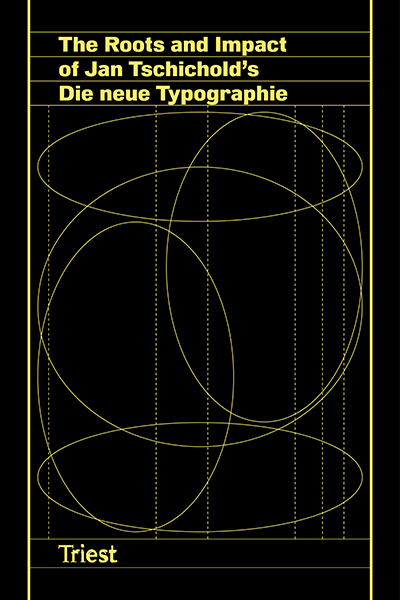
Davide Fornari, Chiara Barbieri, Jonas Berthod (Hrsg.)
The Roots and Impact of Jan Tschichold’s Die neue Typographie (Band 1)
Buchgestaltung: Federico Barbon
• Wo liegt der Urspung zu Tschicholds Werk und welche Strömungen hat es international beeinflusst?
Jan Tschichold war ein bedeutender deutscher Typograf, Buchgestalter und Schriftsteller, der als einer der Pioniere des modernen Grafikdesigns gilt. Geboren 1902 in Leipzig, entwickelte er innovative typografische Prinzipien und setzte sich für klare, funktionale Gestaltung ein. Sein bekanntestes Werk, Die neue Typographie (1928), bildete die Grundlagen des modernen Designs und beeinflusste Generationen von Designern. Tschichold war ein Verfechter der Verwendung von serifenlosen Schriften und einer strukturierten Anordnung von Text und Bild. Nach seiner Emigration aus Deutschland in den 1930er-Jahren setzte er seine Arbeit in der Schweiz und später in Grossbritannien fort, wo er weiterhin die typografische Praxis prägte.
In → Band 1 werden sowohl die Wurzeln, Quellen als auch die Auswirkungen der Neuen Typographie beleuchtet und gezeigt, wie Tschichold auf vorhandene Quellen zurückgriff, um seine eigenen Ideen zu formulieren. Die Essays erforschen die Ursprünge ähnlicher Prinzipien im frühen 20. Jahrhundert in Deutschland, der Tschechoslowakei und Dänemark. Die Publikation zeigt dann die Auswirkungen von Tschicholds Ideen auf die Gestalterszene weltweit, indem sie die Verbreitung, Rezeption und Nachwirkungen von Die Neue Typographie untersucht. Seine Ideen verbreiteten sich unmittelbar in der Schweiz, Grossbritannien und den USA, aber auch verschiedene nationale Szenen in ganz Europa und Asien griffen die Prinzipien der Neuen Typographie auf, wo sie angenommen oder neu verhandelt wurden. Die Publikation ist als thematische multi- und transnationale Geschichte des Grafikdesigns konzipiert, die die Entwicklung von Jan Tschicholds Theorien im Laufe des 20. Jahrhunderts verfolgt. Das Buch erweitert den Rahmen von Die neue Typographie, indem es den zeitlichen Umfang ausdehnt, den geografischen Kontext erweitert und den Diskurs über die Bewegung bereichert.
→ Band 2 widmet sich den Originalquellen von Tschicholds Bibliografie. Er verwendete dafür eine mehrschichtige Logik und organisierte die Quellen nach Typologien (Zeitschriften, Sonderausgaben, Bücher, Normen) und Sprachen. Trotz ihres offensichtlichen Einflusses auf sein Denken blieben diese Quellen aufgrund ihrer Seltenheit und den damit verbundenen Schwierigkeiten bei der Konsultation weitgehend unerforscht. Um dieser Situation entgegenzuwirken, rekonstruiert die vorliegende Publikation den Bestand bibliografischer Quellen, auf die Tschichold zurückgriff, und bietet ein besseres Verständnis des grösseren kulturellen Kontexts von Die neue Typographie. Die Forscherinnen und Forscher identifizierten alle 120 Quellen und sammelten sie, wo möglich, in Original- oder Faksimile-Ausgaben. Band 2 kombiniert diese Forschung mit einer visuellen und textlichen Dokumentation der Referenzen, deren Inhalte in hochwertigen Fotografien mit Beschreibungen, sachlichen Informationen und weiteren Lesemöglichkeiten ergänzt werden.
Mit Beiträgen von Yevgen Anfalov, Andreu Balius, Chiara Barbieri, Sofie Beier, Jonas Berthod, Sandra Bischler-Hartmann, Jessica D. Brier, Christopher Burke, Yongkeun Chun, Catherine de Smet, Davide Fornari, Matthias J.E. Horneman-Thielcke, Lada Hubatová-Vacková, Sandy Jones, Juliet Kinchin, Trond Klevgaard, Sofia Leal Rodrigues, Julia Meer, Emin Artun Ozguner, Louise Paradis, Alyona Sokolnikova, Paul Stirton, Mariko Takagi, Katrien Van Haute, Carlo Vinti, Yun Wang
Über die Herausgeberschaft
Davide Fornari ist ordentlicher Professor an der ECAL/Hochschule für Gestaltung und Kunst Lausanne (HES-SO), wo er seit 2016 den Bereich der angewandten Forschung und Entwicklung leitet.
Chiara Barbieri ist Forscherin für Designgeschichtean der ECAL/Hochschule für Kunst und Design Lausanne (HES-SO). Sie promovierte in Designgeschichte am Royal College of Art (London) mit einer Arbeit über die Professionalisierung des Grafikdesigns
in Italien von der Zwischenkriegszeit bis Mitte der 1960er-Jahre.
Jonas Berthod arbeitet als Forscher, Dozent und künstlerischer Stellvertreter an der ECAL/Hochschule für Gestaltung und Kunst Lausanne (HES-SO), wo er seit 2013 unterrichtet. Er promovierte an der Universität Bern mit der Arbeit The Prize of Success (Transcript, 2024) über den Einfluss der Kulturförderung auf das Schweizer Grafikdesign.